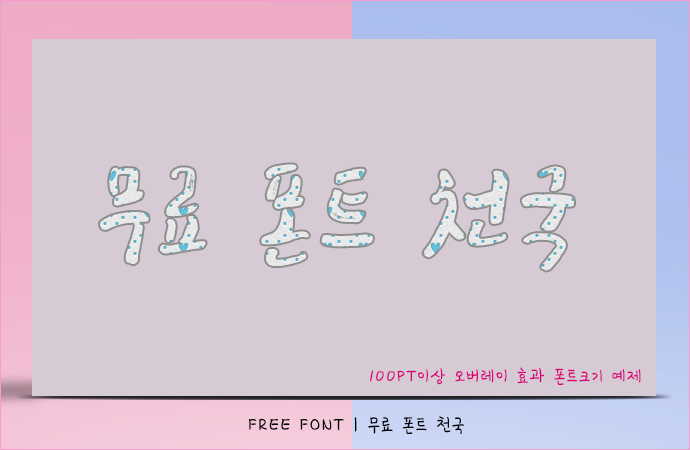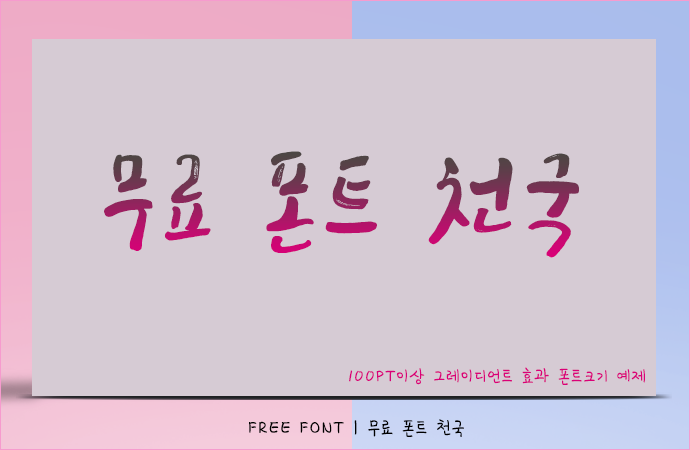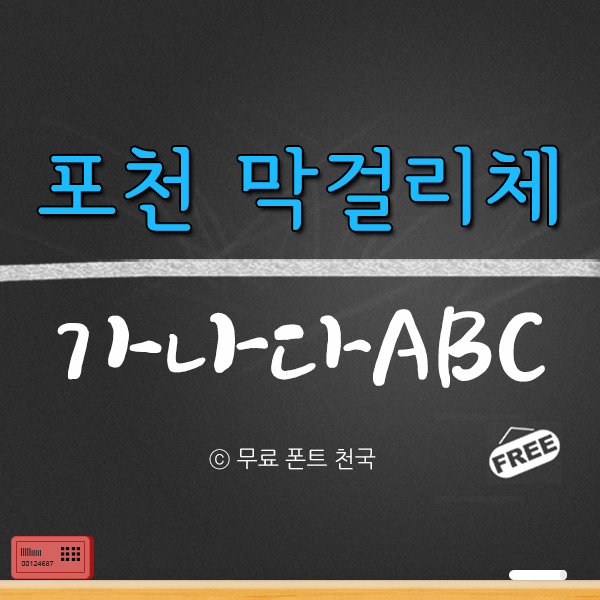
전통적인 느낌의 포천 막걸리체 폰트
포천시에서 무료로 배포하는 '포천 막걸리체'는 섬세하고 부드러운 느낌을 표현할 때 자주 사용되는 서체입니다. 작은 글씨체를 비롯해 큰 글씨체에서도 가독성이 매우 좋은 서체입니다. 개인 및 기업과 공공기관 그리고 학교 등에서도 누구나 제한 없이 사용 가능한 서체입니다. 단 인쇄물을 목적으로 사용될 경우에는 저작권 (포천시 서체)을 밝히고 사용하셔야 합니다.
포천 막걸리체 폰트 # 미리보기
포천 막걸리체 폰트, 12~80PT 크기로 적용한 효과
포천 막걸리체 폰트, 100PT 크기 이상으로 작업한 오버레이 효과
포천 막걸리체 폰트, 100PT 크기 이상으로 작업한 그레이언트 효과